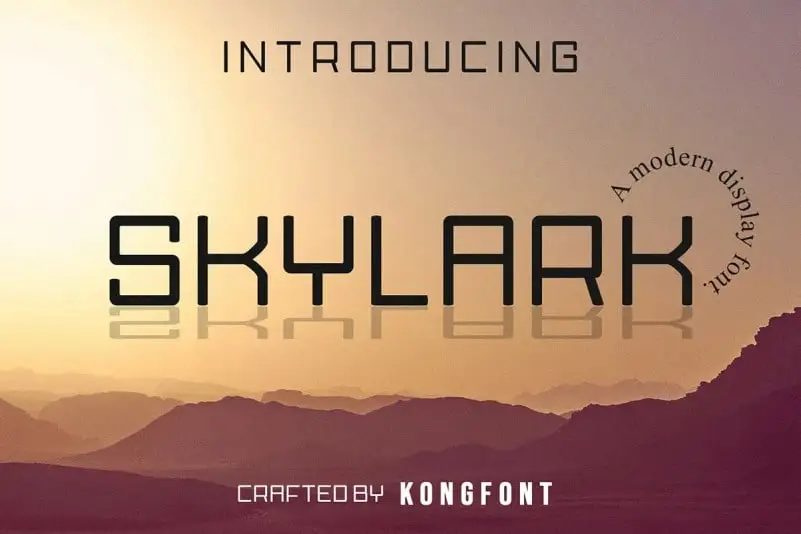
Skylark Display Font – Download Grátis
A fonte Skylark Display é uma seleção minimalista, clássica e impressionante, projetada sobretudo para usos visuais onde a presença visual é crucial. Esta fonte está disponível apenas em maiúsculas, oferecendo um estilo moderno sem ser serifado e criada especialmente por fontkong para usar na propaganda cinematográfica, headlines, letras de blocos, subtítulos, logomarcas e bandeiras grandes. Seu design clássico e decorativo é perfeito para ambientes de web que exigem um design visual atraente e memorável. Ideal tanto para estilos digitais quanto impressos, esta fonte é uma escolha ótima para designers buscando transmitir sua mensagem em um formato impactante e moderno.